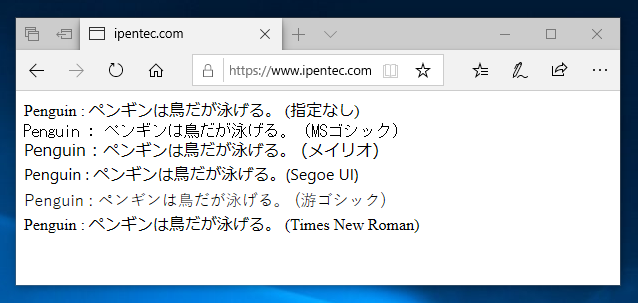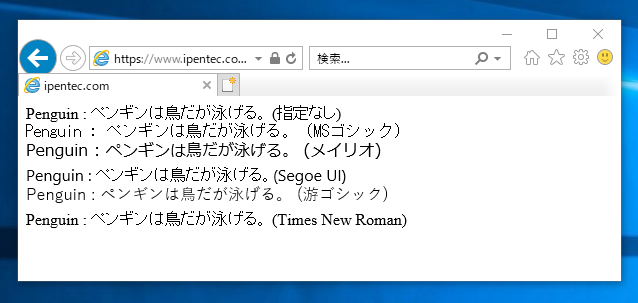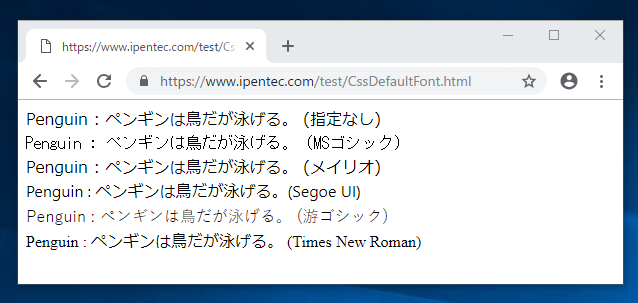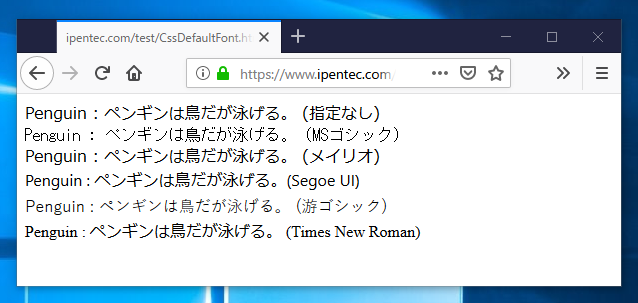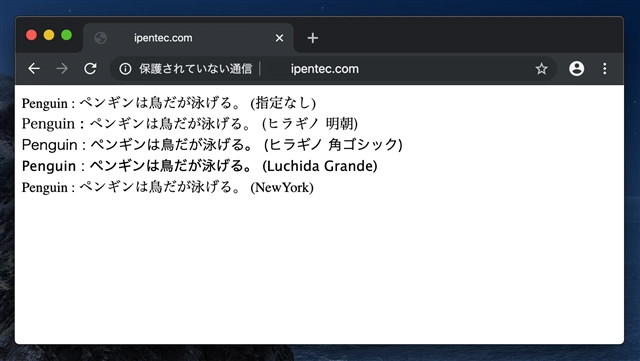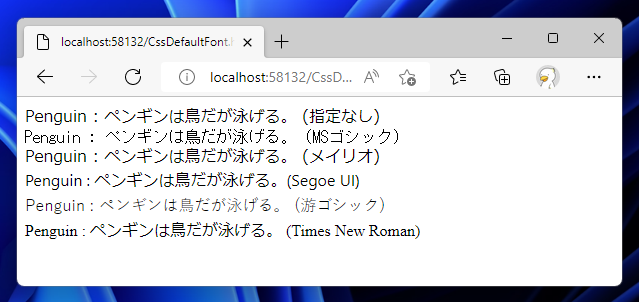
HTMLでfontを指定しない場合に描画に使用されるフォントを紹介します。
以下の動作になります。
Webブラウザ | 英数文字 | 日本語文字 |
---|---|---|
Microsoft Edge | メイリオ | メイリオ |
Microsoft Internet Explorer | Times New Roman | MS Pゴシック |
Google Chrome | メイリオ | メイリオ |
Mozila Firefox | メイリオ | メイリオ |
Microsoft Edge(旧) | Times New Roman | メイリオ |
Webブラウザ | 英数文字 | 日本語文字 |
---|---|---|
Safari | New York | ヒラギノ 明朝 (W3) |
Google Chrome | New York | ヒラギノ 明朝 (W3) |
下記のHTML, CSSファイルを作成します。
上記のHTMLファイルをWebブラウザで表示します。
指定なしの日本語文字がMSゴシックのフォントより詰まって表示されており、MS Pゴシックの表示であることがわかります。
下記のHTML, CSSファイルを作成します。
上記のHTMLファイルをWebブラウザで表示します。